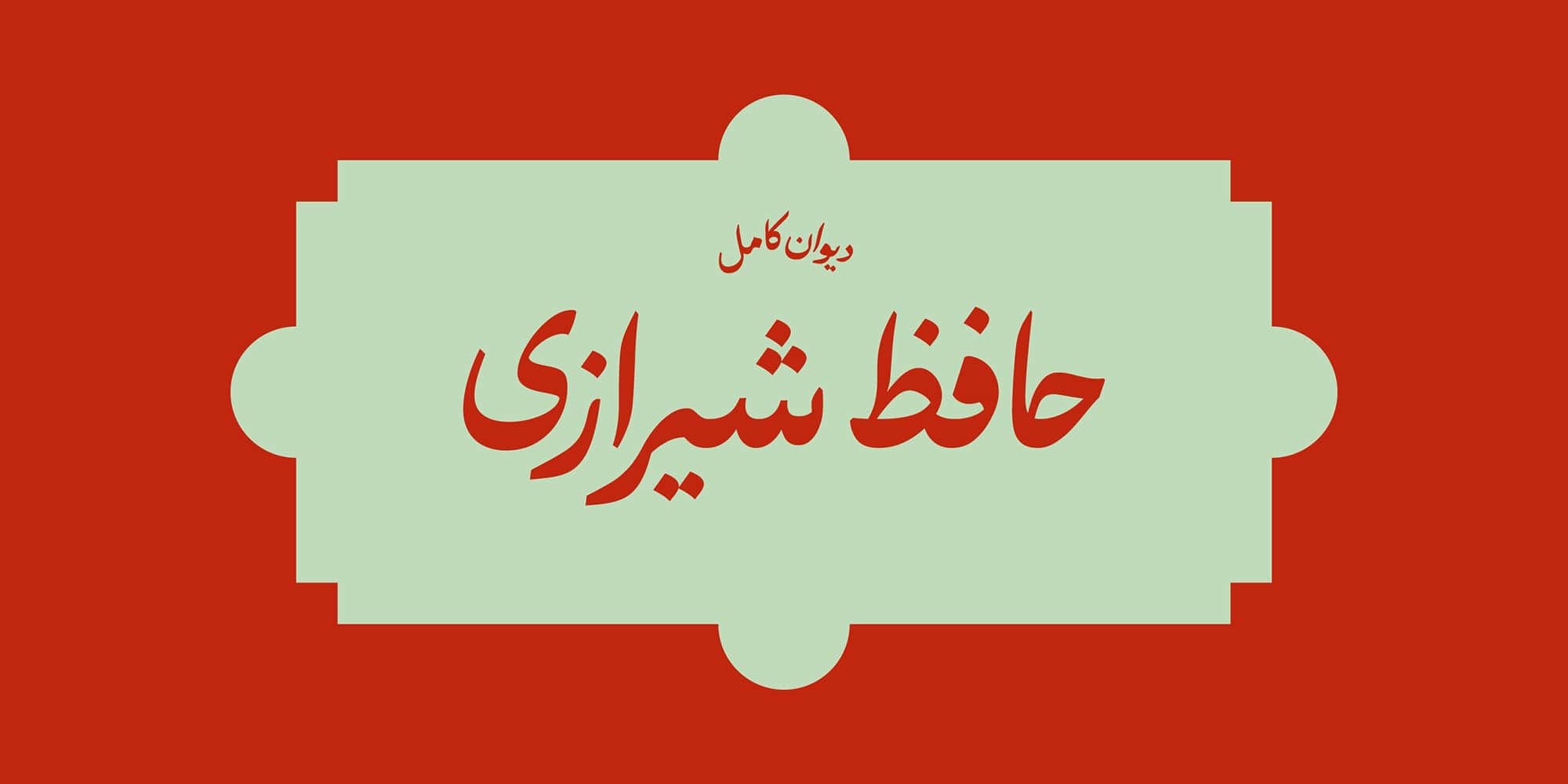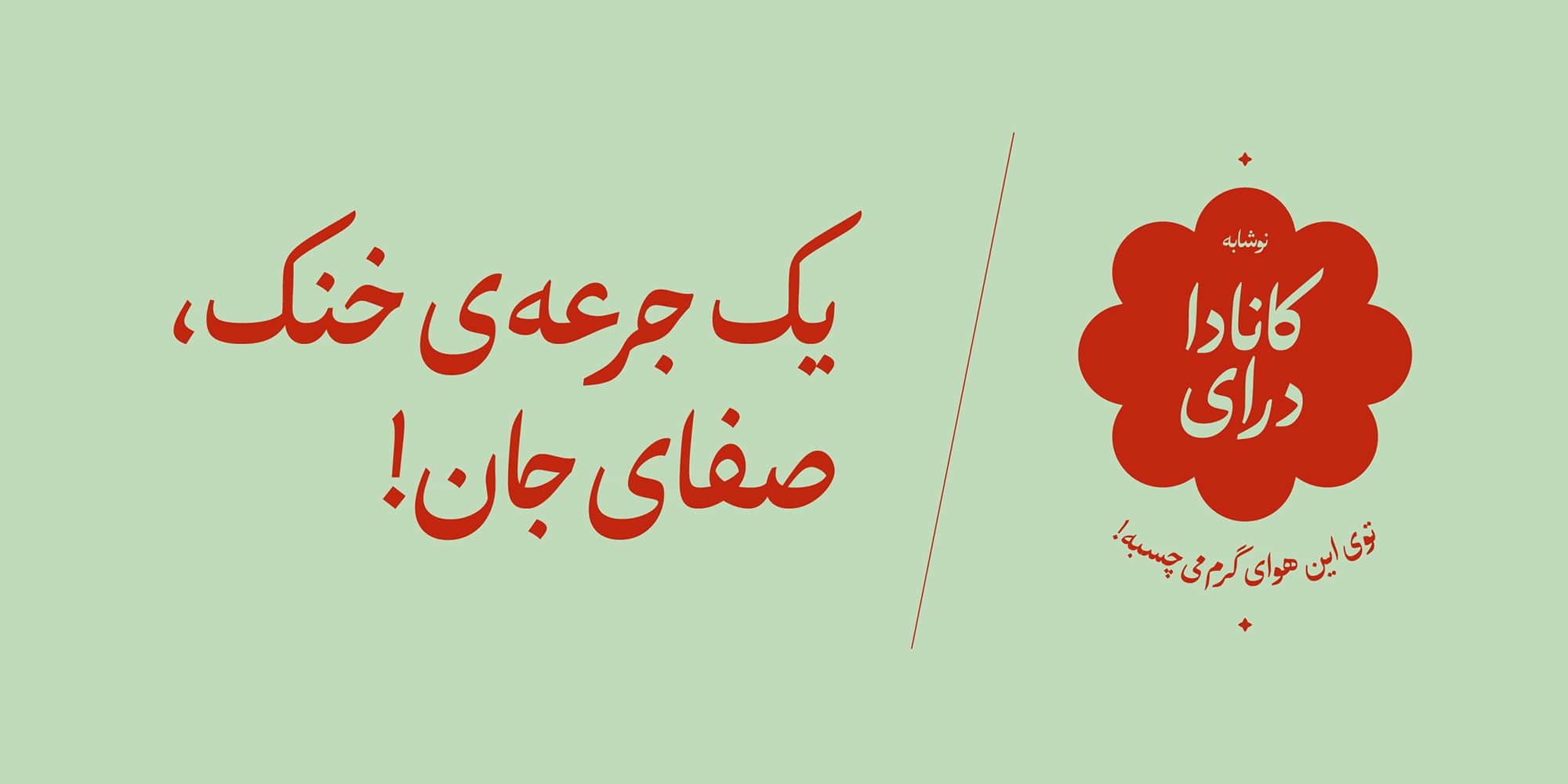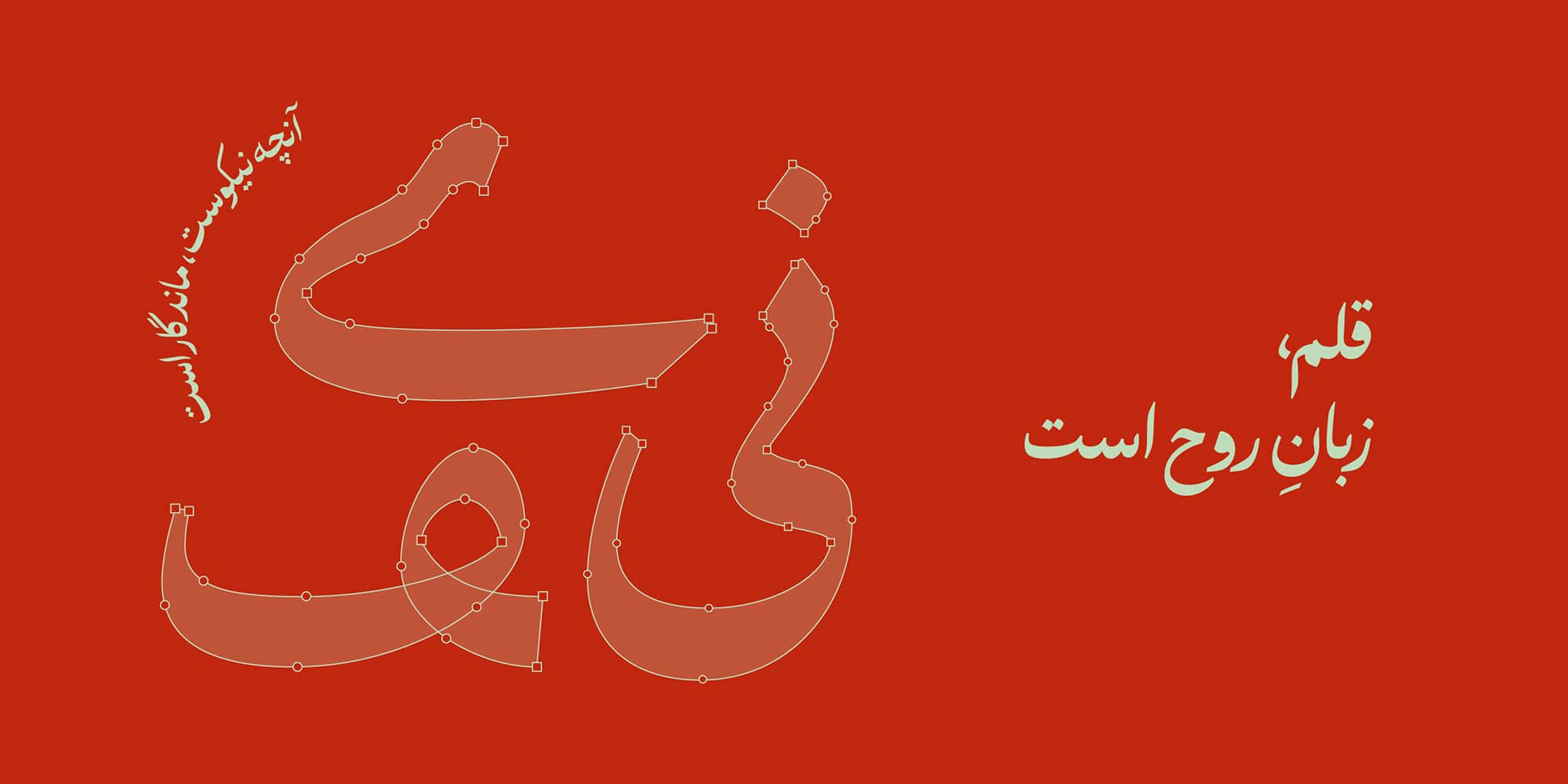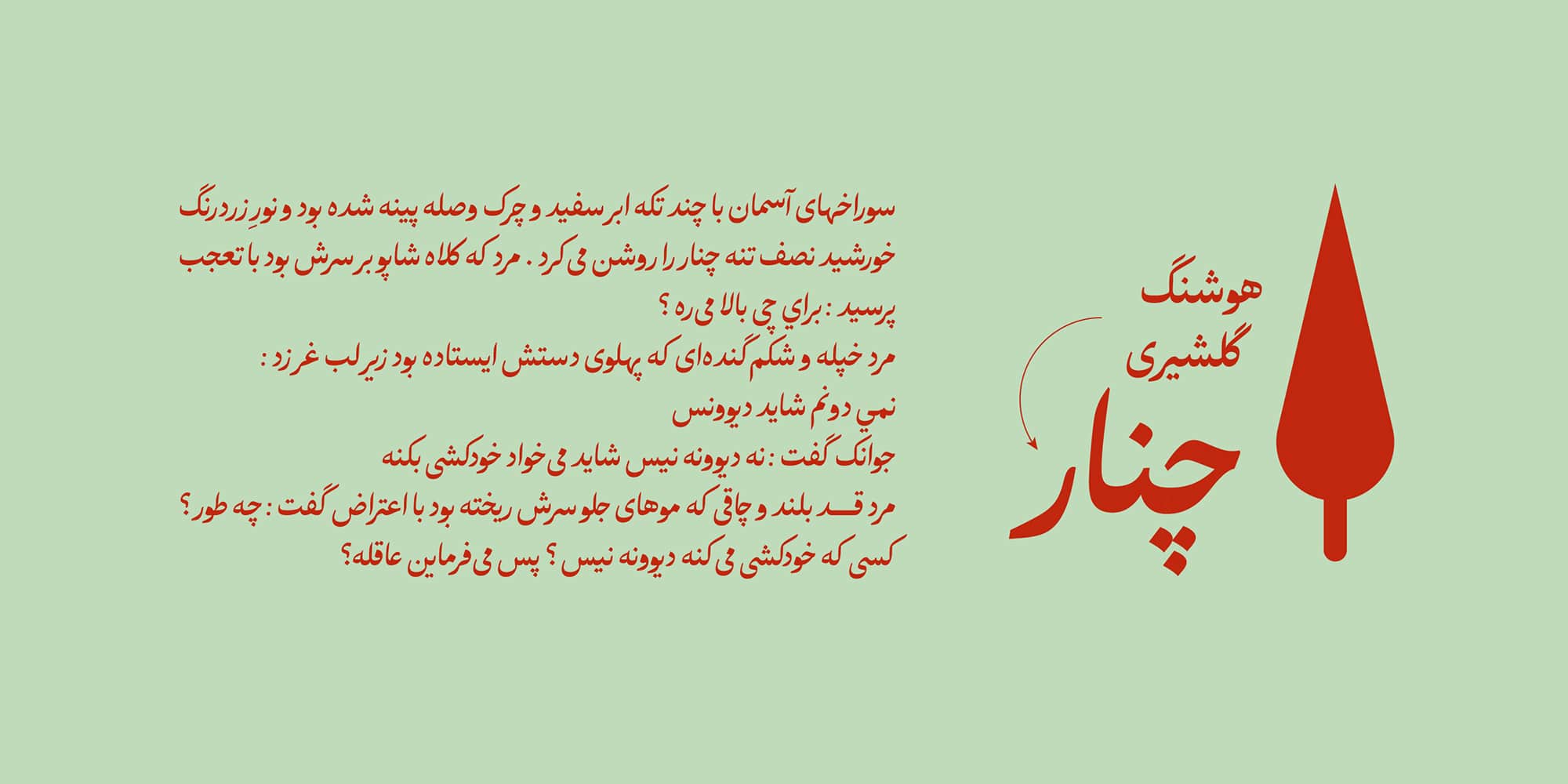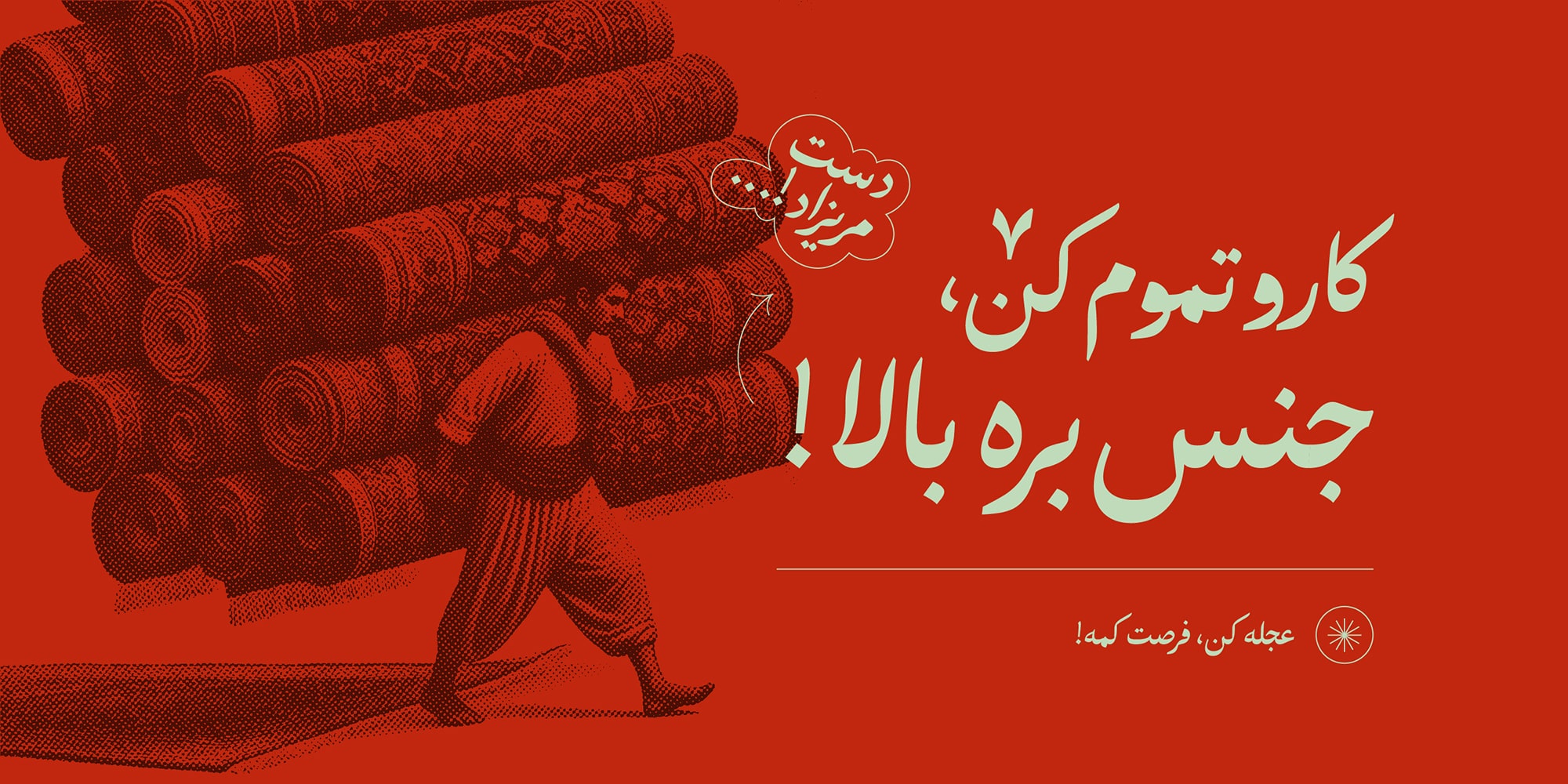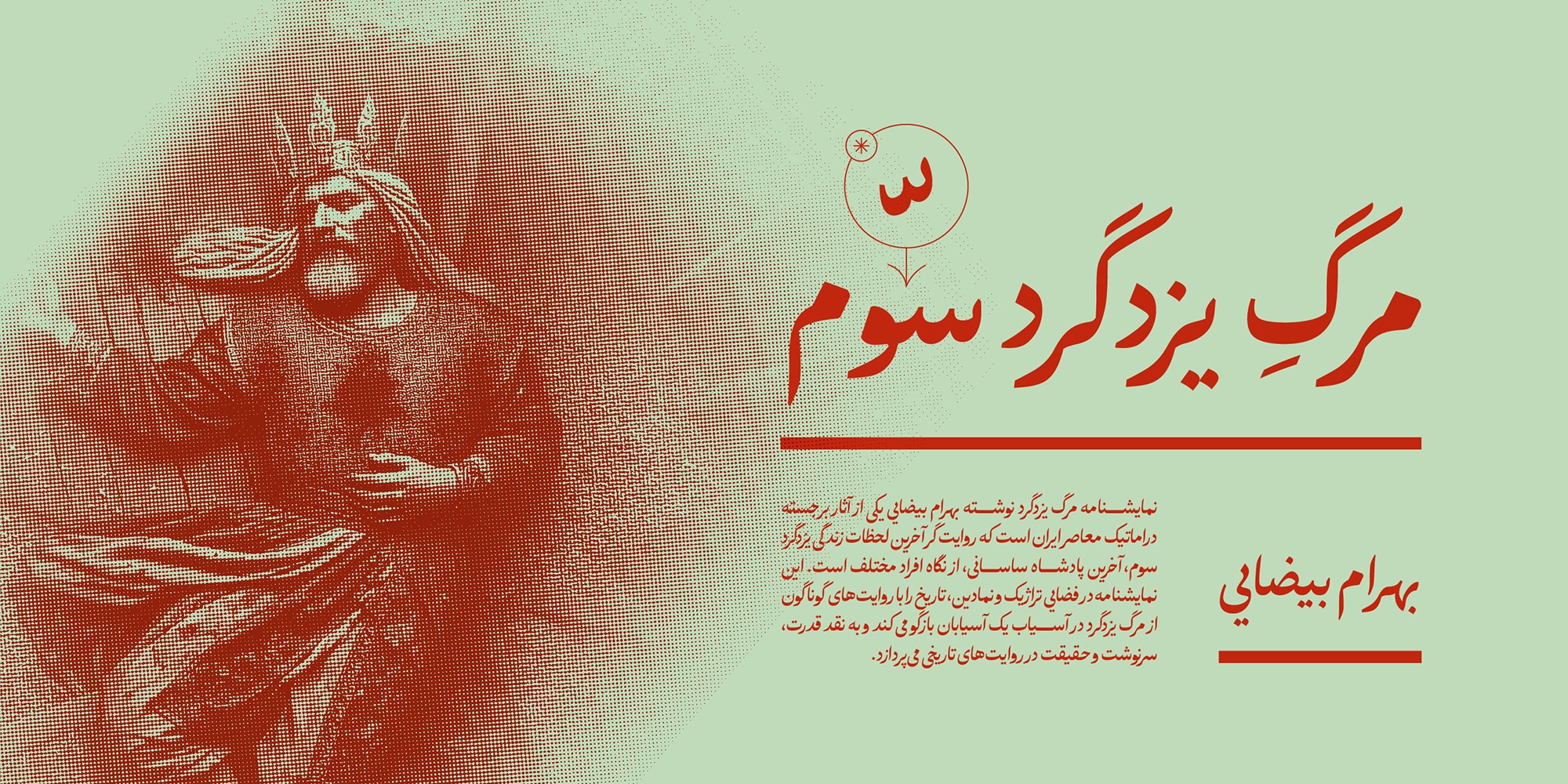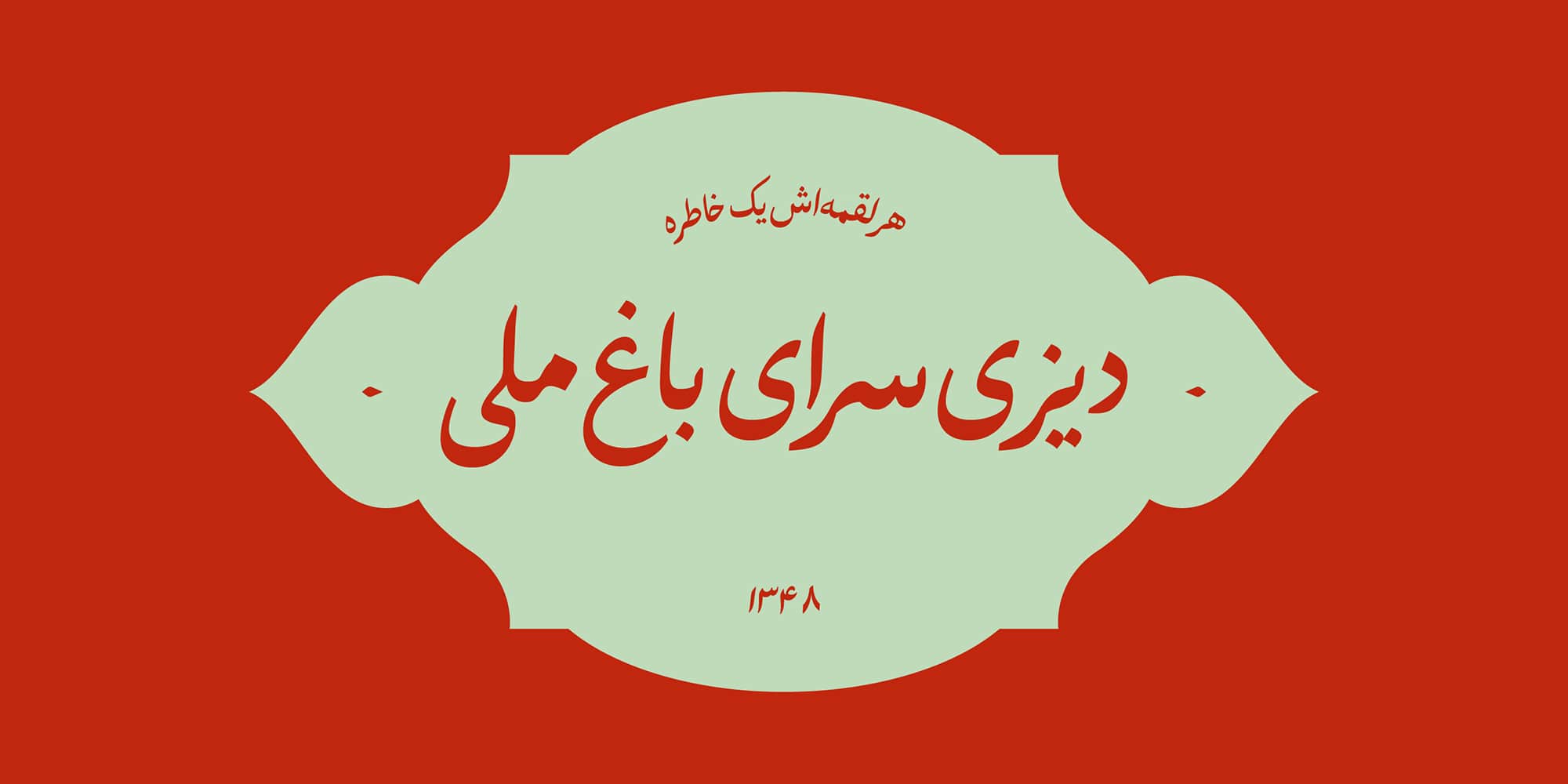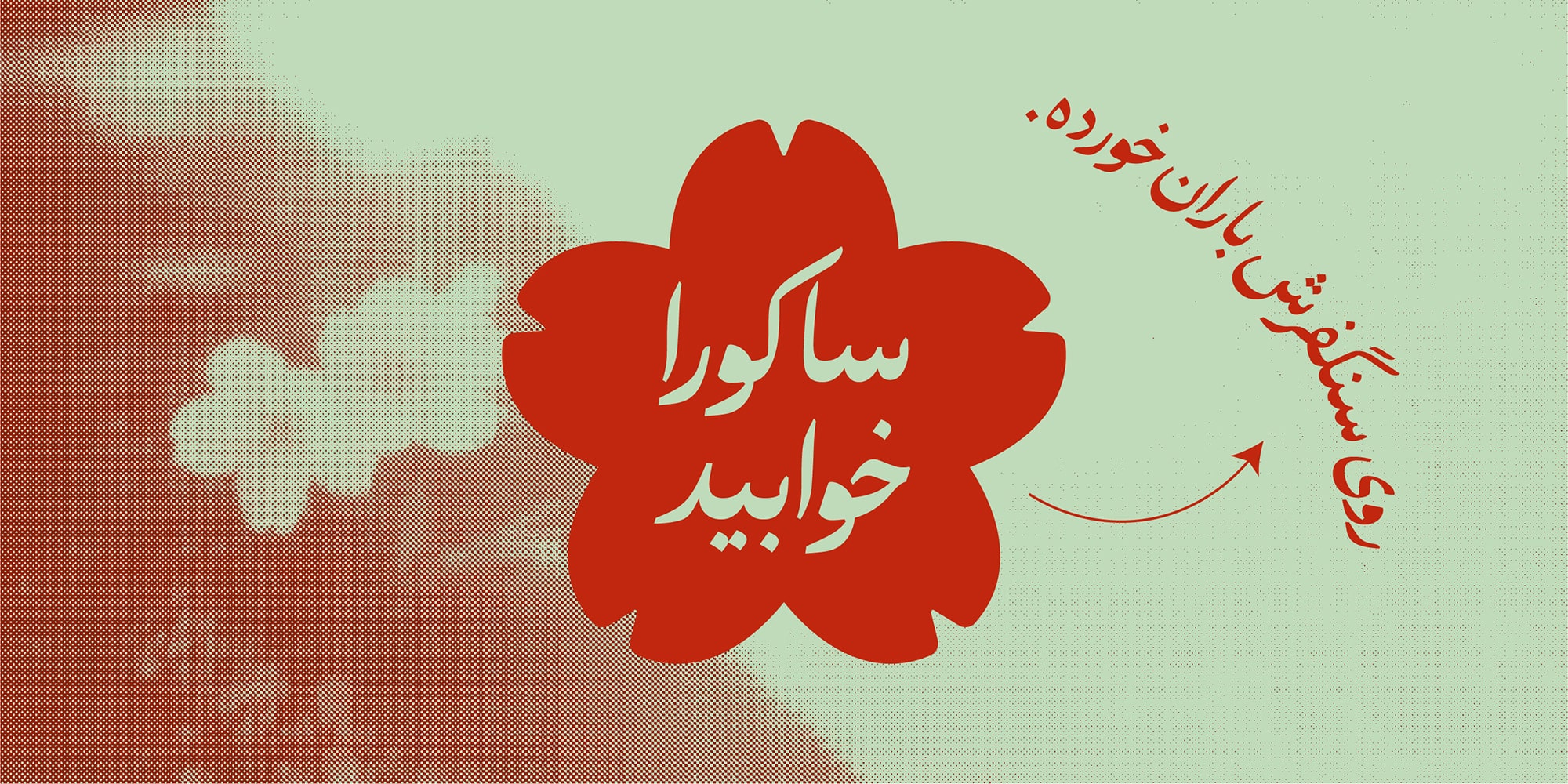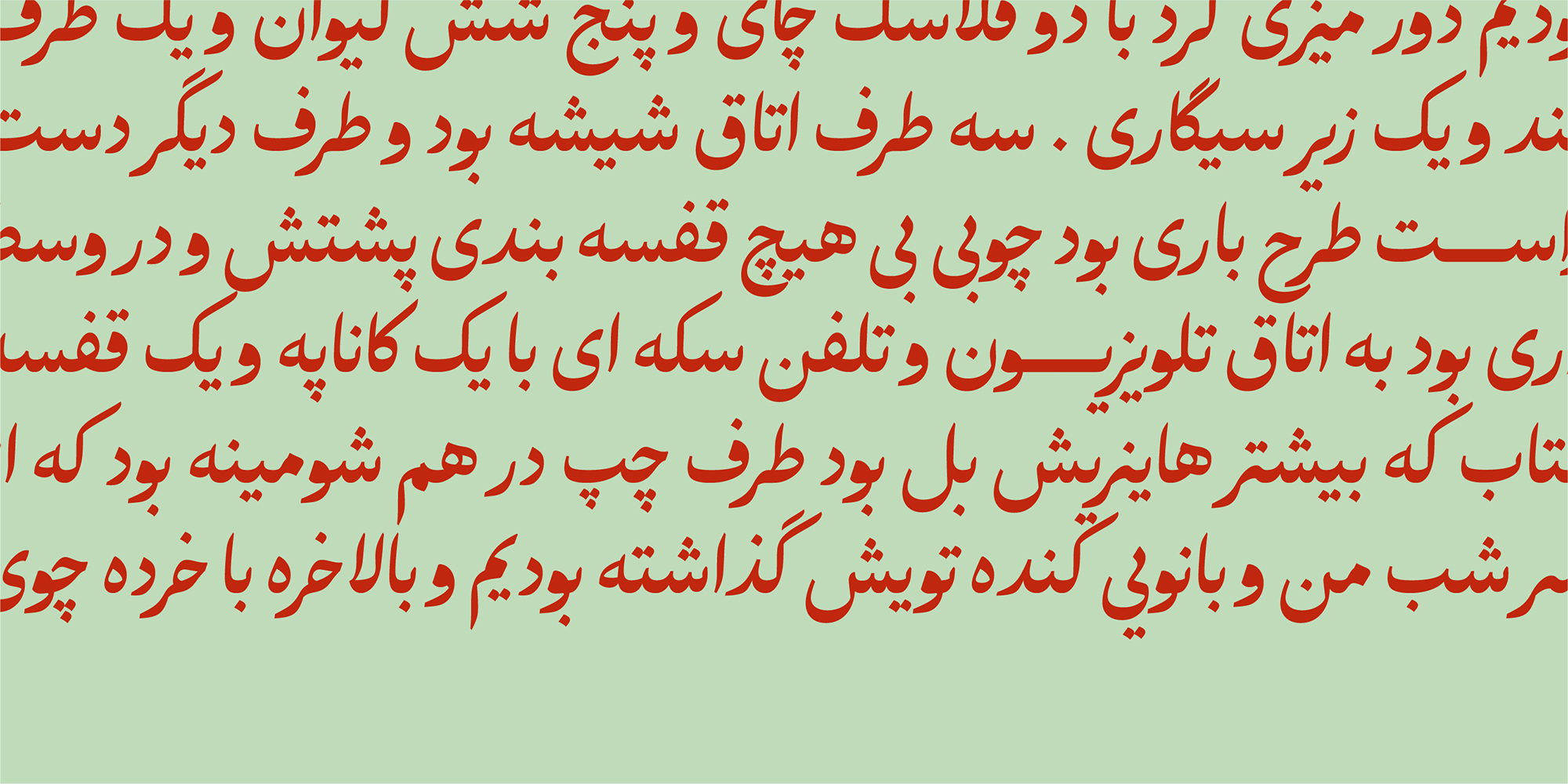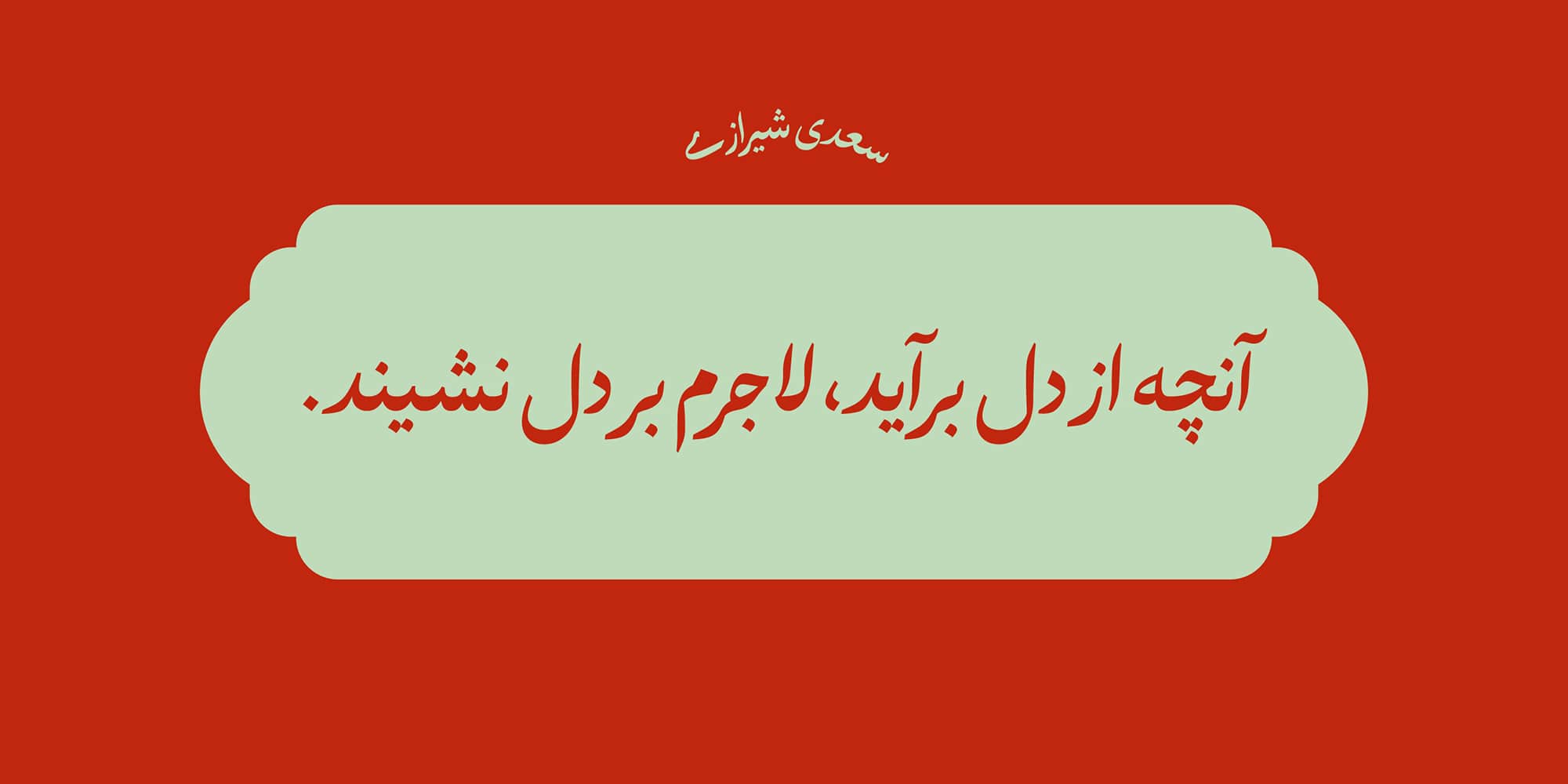
فونتی که از دل سنت، به دنیای معاصر سلام میکند.
فونت «حافظ» با الهام از دو ستون باشکوه خوشنویسی ایرانی، یعنی خط نستعلیق و خط نسخ، خلق شده است. در طراحی این فونت، تلاش شده تا با حفظ اصالت و روح خطوط کلاسیک، خوانایی و نظم خط نسخ با لطافت و جریان شاعرانهی نستعلیق در هم آمیزد؛ ترکیبی که در نهایت به خلق قلمی منتهی شده که زیبایی سنت را با کاربردهای نوین پیوند میزند.
از ویژگیهای چشمگیر این فونت، قرارگیری خاص و دقیق فرمهای نستعلیق بر روی خط کرسی است؛ حرکتی که باعث شده ساختار این فونت در عین زیبایی، منسجم و متعادل باقی بماند. «حافظ» نه تنها به لحاظ بصری چشمنواز است، بلکه کاربردی و انعطافپذیر نیز هست.
زمینههای کاربردی فونت حافظ گستردهاند: از پروژههای فرهنگی و هنری گرفته تا آثار ادبی، فلسفی و رسانههایی با تم تهران قدیم، سنت، حکمت و وقار. این فونت به خوبی میتواند حس اصالت، دانایی و تاریخ را منتقل کند و در عین حال برای فضای دیجیتال و چاپی بهروز باقی بماند.
حافظ، نه تنها یک تایپفیس، بلکه یک پل میان گذشتهی زرین و حال پرشتاب ماست.